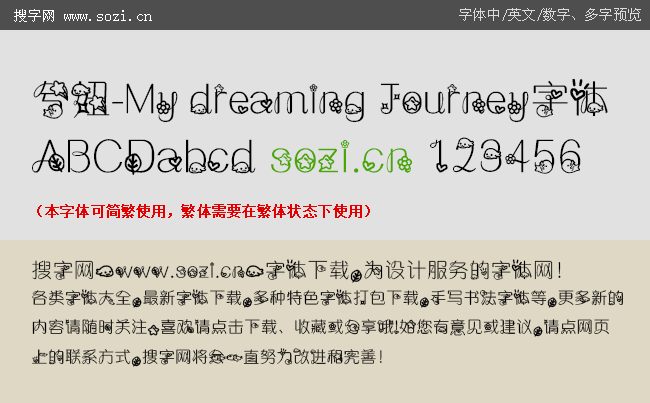
My dreaming Journey字體
搜字網(wǎng)給大家提供一款很有趣的手機(jī)中文字體下載。字體名字叫My dreaming Journey字體,這款手機(jī)字體是在纖蘭字體筆畫間插入了大量的卡通圖案。纖蘭字體是面向港臺(tái)地區(qū)的字體,字形端正大方,精致悅目,加入花紋后增強(qiáng)了趣味性,特別適合喜歡手機(jī)字體個(gè)性一些的朋友在手機(jī)上安裝使用。